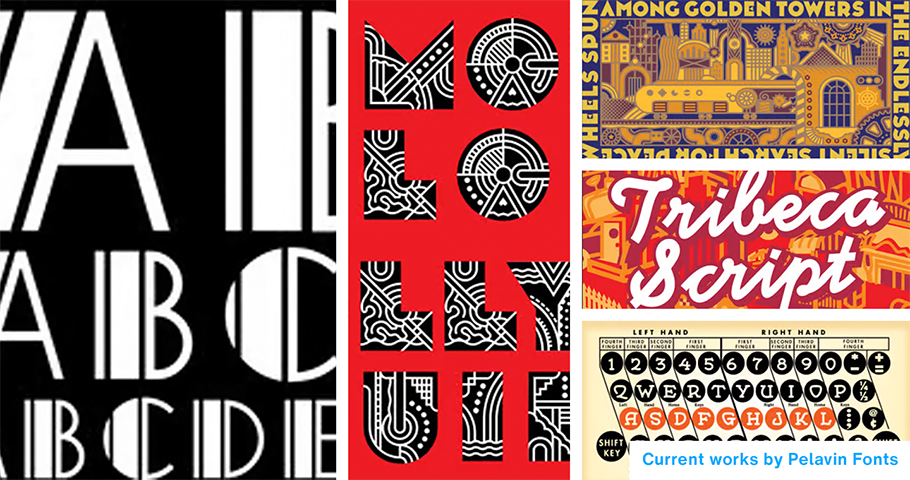
Im Inneren des Studios: Creative Characters - Pelavin Fonts
Tagen Wenn Sie sich mit dem Illustrator und Typografen Danny Pelavin unterhalten, werden Sie feststellen, dass er dankbar dafür ist, dass er in den 1970er Jahren, in der Blütezeit der Designstudios in Detroit, kreativ erwachsen geworden ist, dass er immer noch alle seine Schriftzüge von Hand macht und dass er sich nicht scheut, Über seine Wahrheiten mitzuteilen.
Als Gewohnheitsmensch des Satzes "Ich muss ehrlich zu Ihnen sein" gibt er zu, dass Prokrastination Teil seines Arbeitsprozesses ist, und gesteht, dass er befürchtet, ein Betrüger zu sein. Dennoch hat er viele Erfolge zu verzeichnen. Seit er 1979 nach Manhattan gezogen ist, hat er regelmäßig Zeichnungen für die New York Times, das Wall Street Journal, Fortune und andere veröffentlicht.
In einem kürzlich geführten Interview mit Monotype sprach er über seinen beruflichen Werdegang, die Veränderungen in seiner Branche und die Möglichkeiten für die Zukunft.
MyFonts (MF): Sie haben Ihre Anfänge in Detroit gemacht, wo Sie geboren wurden. Wann haben Sie zum ersten Mal erkannt, dass visuelle Details - Zeichnungen - Bedeutung und Wichtigkeit haben?
Daniel Pelavin (DP): Ich war 4 oder 5 Jahre alt - ich hing mit meiner Tante Rose herum, die meiner Mutter eine Pause gönnte - und sie ging zur Bank und füllte einen Einzahlungsbeleg aus. Ihre Schrift auf dem Papier machte mich neugierig auf Menschen, die Buchstabenformen zur Kommunikation verwenden. Es ging nicht nur um die Typografie, sondern auch um die Zeichen, die von Hand gemacht wurden. Das ist mir wichtig, denn kein Schriftzug entsteht, ohne dass eine Hand dahinter steckt.
MF: Wann haben Sie begonnen, Künstler zu werden?
DP: Vierte Klasse. Aufgrund meines [ADS-bedingten] Verhaltens schlug meine Schule vor, dass ich das Oakland County Child Guidance Center besuchen sollte. Dort gaben sie mir Puzzles, bei denen man die Form Nächste vorhersagen musste. Aber ich bin ein großer Fan davon, wie Formen zusammenpassen und welche Bedeutung sich aus ihrer Zusammensetzung ergibt.
Später wurde ich in einen Kurs für industrielles Zeichnen eingeteilt, der, wie ich glaube, von ehemaligen Marinesoldaten geleitet wurde. Ich hatte mein Dreieck, meine französische Kurve, meinen Zeichenpinsel, und ich verbrachte meine Zeit damit, die Formen so perfekt wie möglich zu gestalten. All diese Dinge hatten einen sehr großen Einfluss.
Größer jedoch waren meine 3,5 Jahre Atelierpraktika nach dem College. Sobald ich eingestellt war, betrat ich Räume voller arbeitender Künstler und bombardierte sie mit Fragen, bis sie mich hinauswarfen. Dort habe ich wirklich gelernt, wie man ein Künstler wird - nicht an einer Universität.
MF: Interessanterweise waren Sie später selbst als Hochschullehrer tätig, unter anderem am FIT, an der Syracuse University und jetzt an der University of Hartford?
DP: Ja. Ich derzeit unterrichte in einem MFA-Programm für Illustration mit begrenztem Aufenthalt. Es ist amüsant, Leuten beizubringen, wie man im Jahr 2023 illustriert, da die aktuellen Trends in der Branche diese Fähigkeit nicht brauchen. Aber was ich lehre, ist sehr spezifisch. Ich zeige den Leuten nicht, wie sie etwas machen sollen. Ich ermutige sie, das zu lieben, was sie tun müssen, weil ich weiß, dass sie das dazu antreibt, sich anzustrengen, um etwas zu erreichen.
MF: Erzählen Sie mir Über Ihr eigenes Design oder Kunstwerk.
DP: Ich kann über Über Salty Dog sprechen. Das ist meine Neuauflage einer klassischen Buchstabenform, die seit Jahrhunderten verwendet wird und bei der die Buchstaben aus einem Seil hergestellt werden. Salty Dog bezieht sich auf Seeleute, die Knoten knüpfen, aber es funktioniert auch für westliche Menschen, die Lariats machen.
MF: Wie sieht Ihr kreativer Prozess aus?
DP: Wenn ich einen Auftrag bekomme, prokrastiniere ich erst einmal. Ich suche nach Stichworten für Bilder, die ich manchmal auf Moodboards ausdrucke. Die Leute denken: "Toll, jetzt hast du dieses Blatt, das dich in deinem Prozess leiten wird". Und ich sage: "Nein, jetzt zerreißt du das Blatt und wirfst es weg." Denn die Suche füllt den Kopf mit dem, was man braucht, um die Arbeit zu erledigen.
Dann schiebe ich noch mehr auf. Ich schaue in meinem Kalender nach, wann ich spätestens fertig werden kann. Dann öffne ich dieses Aquabee Super Deluxe Skizzenbuch, das ich so liebe. Ich zeichne mit einem Füllfederhalter. Die einzige Möglichkeit, Tinte "rückgängig" zu machen, ist, sie zu überdecken. Ich mache Dutzende von groben Skizzen, von denen ich denke, dass sie das darstellen, was der Kunde sucht. Nachdem sie sich für eine entschieden haben, versuche ich, sie davon abzuhalten, ihre eigene Arbeit zu sabotieren, indem sie an sich selbst zweifeln. Kunden, die an sich selbst zweifeln, zweifeln auch an Ihnen.
MF: Auf welche Arbeit sind Sie am stolzesten?
DP: Das ist so schwer. Auf meiner Website Webseite, DanielPelavin.com, gibt es mehr als ein paar Projekte, auf die ich sehr stolz bin. Aber es gibt auch wesentlich mehr als ein paar, die ich beweine und für die ich mich schäme.